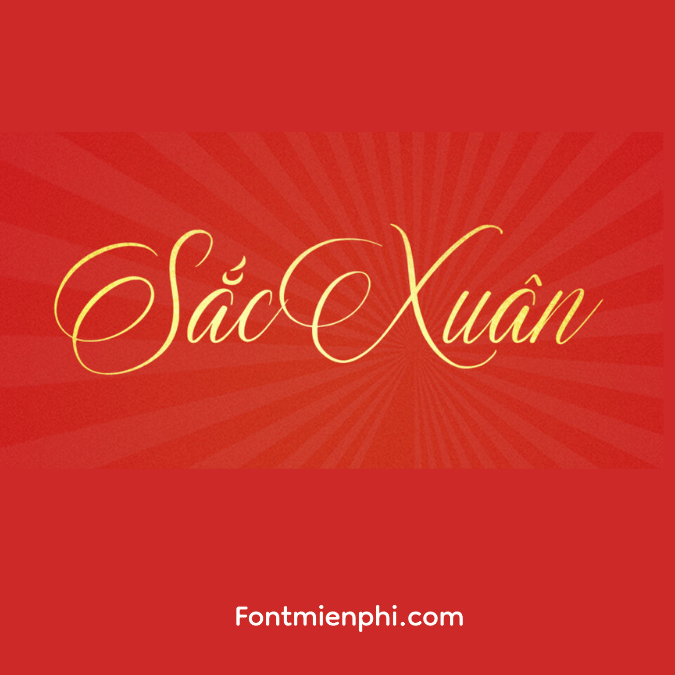
Việt Hóa 1FTV VIP Westwood Studio
Font 1FTV VIP Westwood Studio là một kiểu chữ hiện đại và sang trọng, thường được sử dụng trong thiết kế đồ họa, quảng cáo và các sản phẩm truyền thông. Font này mang lại cảm giác tinh tế và chuyên nghiệp, phù hợp với nhiều loại hình nội dung khác nhau.
- Đặc điểm:
- Thiết kế chữ cái rõ ràng, dễ đọc.
- Có nhiều kích thước và trọng lượng khác nhau để phù hợp với nhiều mục đích sử dụng.
- Cung cấp đầy đủ các ký tự tiếng Việt, giúp người dùng dễ dàng sử dụng trong các dự án liên quan đến văn bản tiếng Việt.
Font Tết là một kiểu chữ đặc biệt được thiết kế nhằm phục vụ cho các dịp lễ Tết cổ truyền của người Việt. Font này thường có những họa tiết trang trí mang đậm tính văn hóa và phong tục tập quán của người Việt.
- Đặc điểm:
- Thường có các họa tiết hoa mai, hoa đào, hay các biểu tượng liên quan đến Tết như bánh chưng, bánh tét.
- Màu sắc thường rực rỡ, nổi bật, tạo không khí vui tươi, phấn khởi cho mùa lễ hội.
- Được sử dụng phổ biến trong thiệp chúc Tết, banner quảng cáo và các sản phẩm trang trí trong dịp Tết Nguyên Đán.
Hai kiểu font này đều có giá trị thẩm mỹ cao, góp phần làm phong phú thêm cho văn bản và hình ảnh trong các dự án thiết kế.